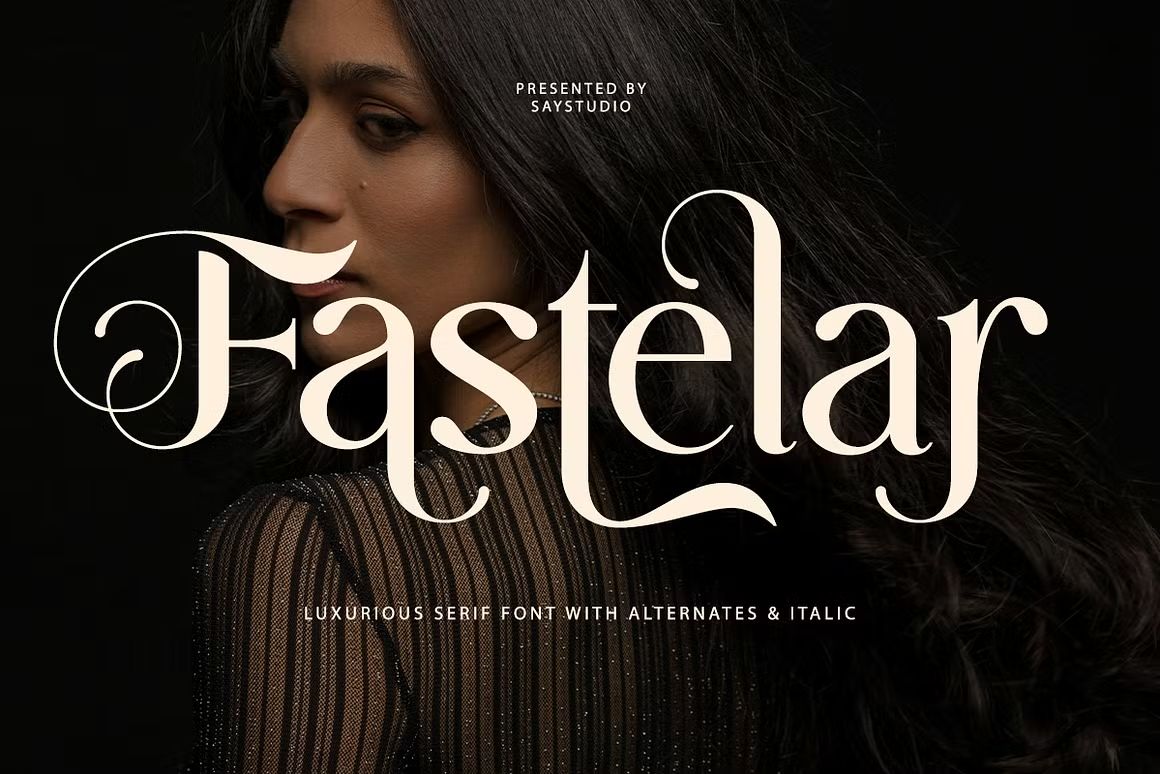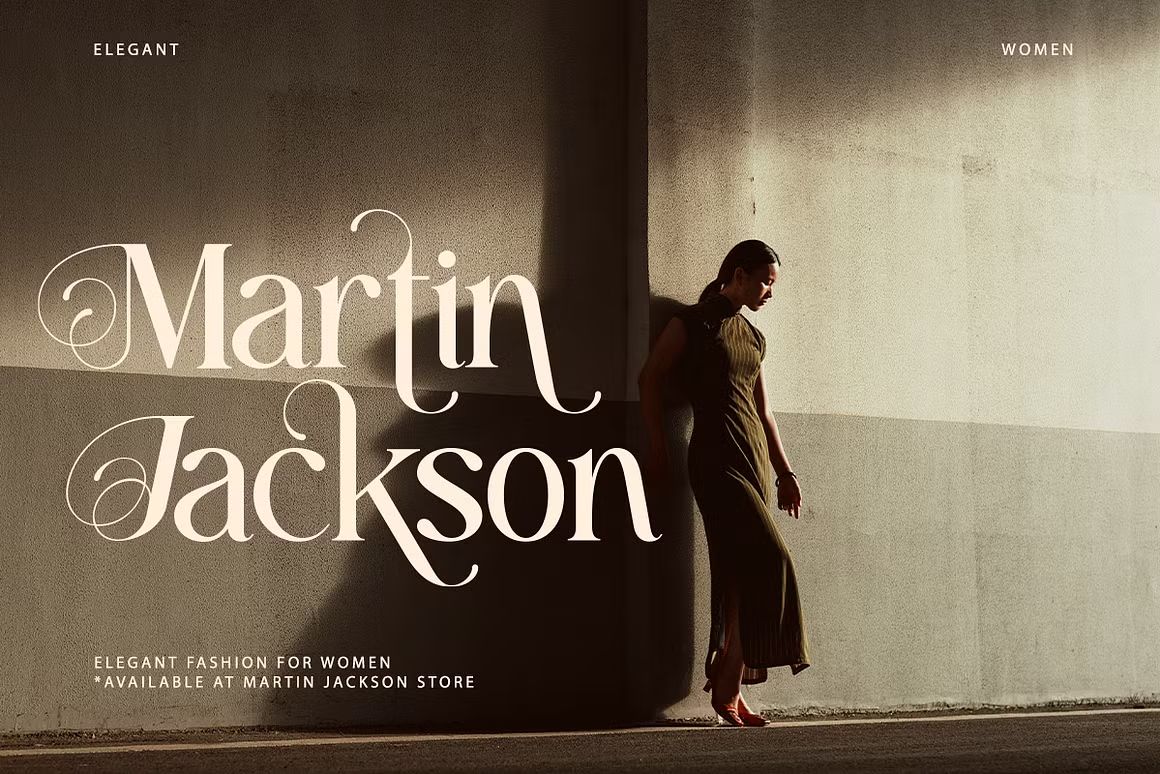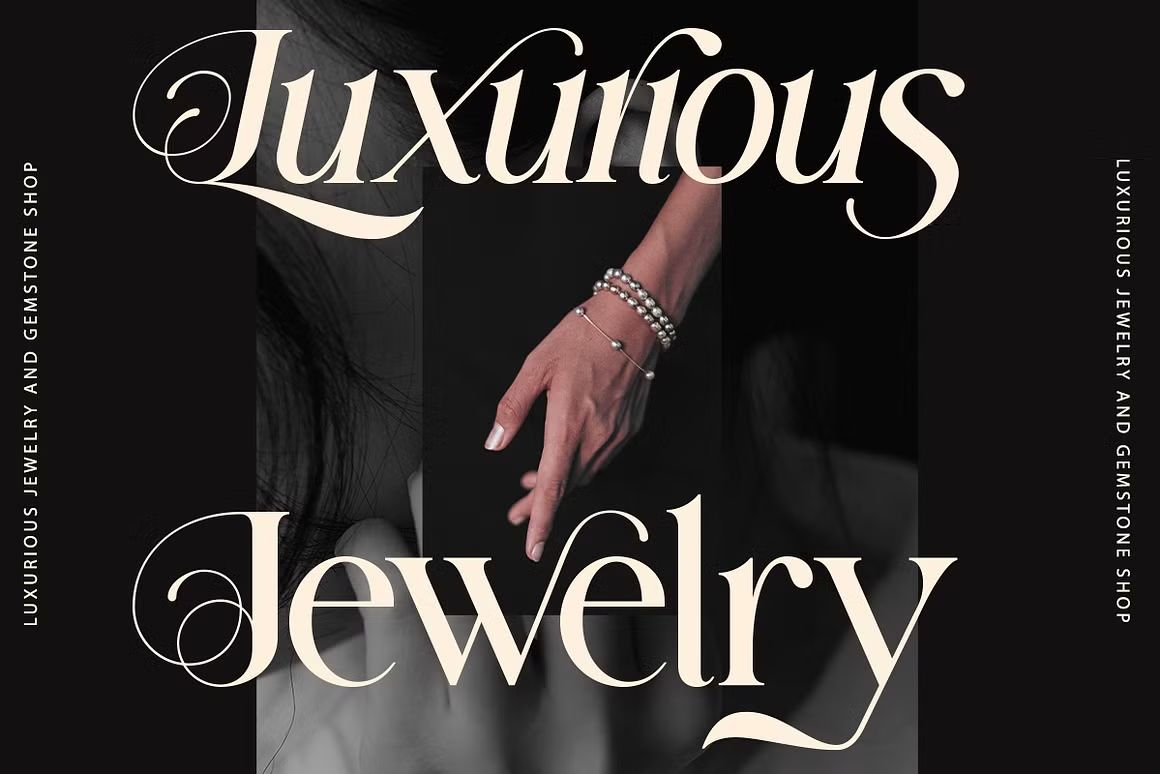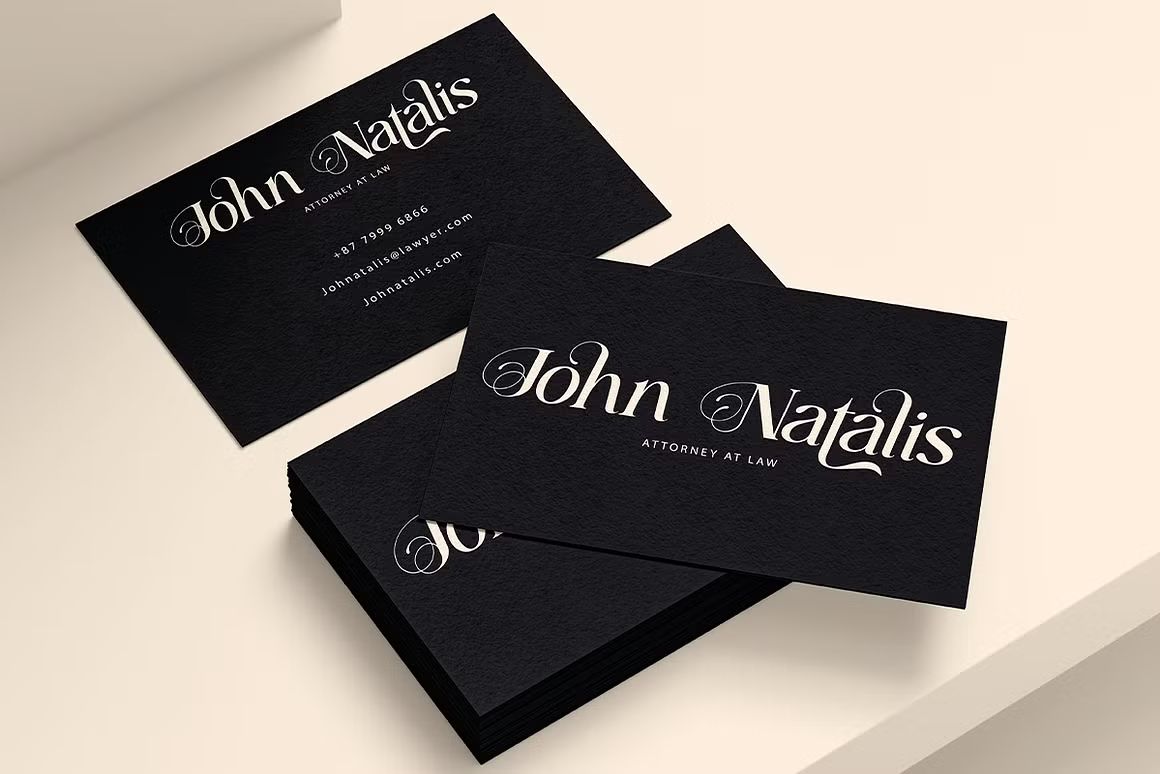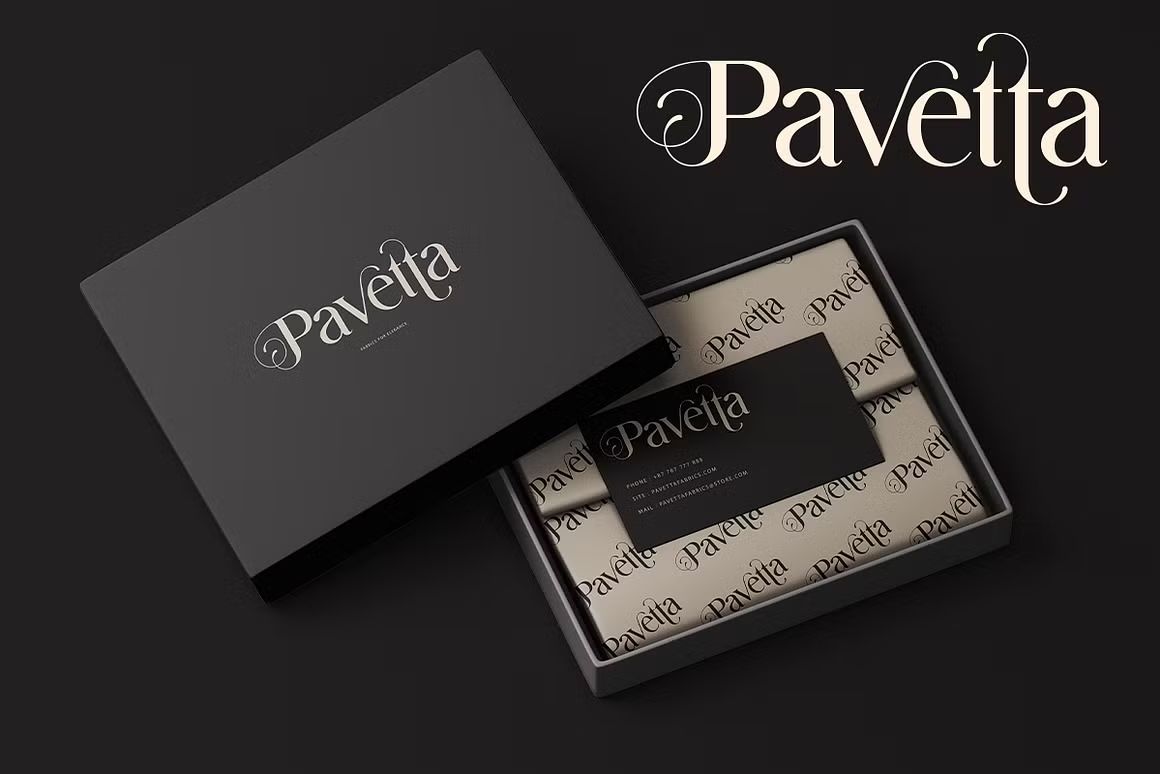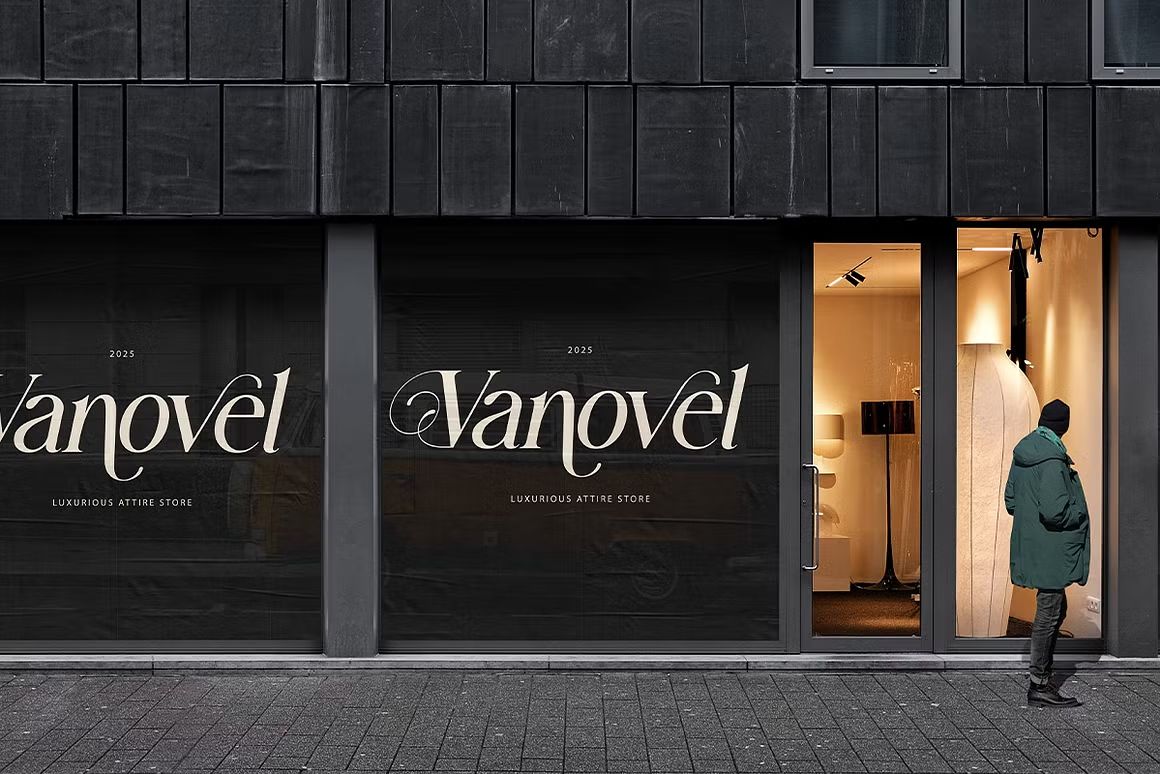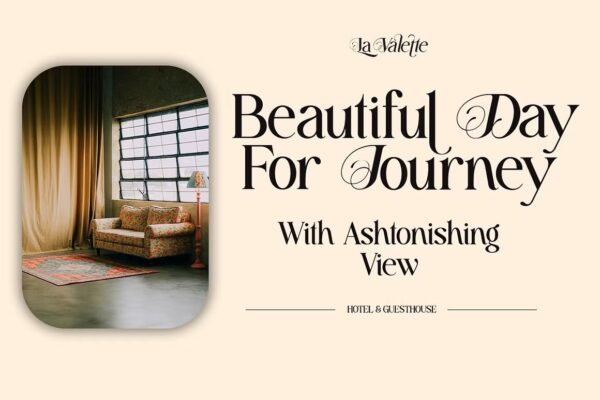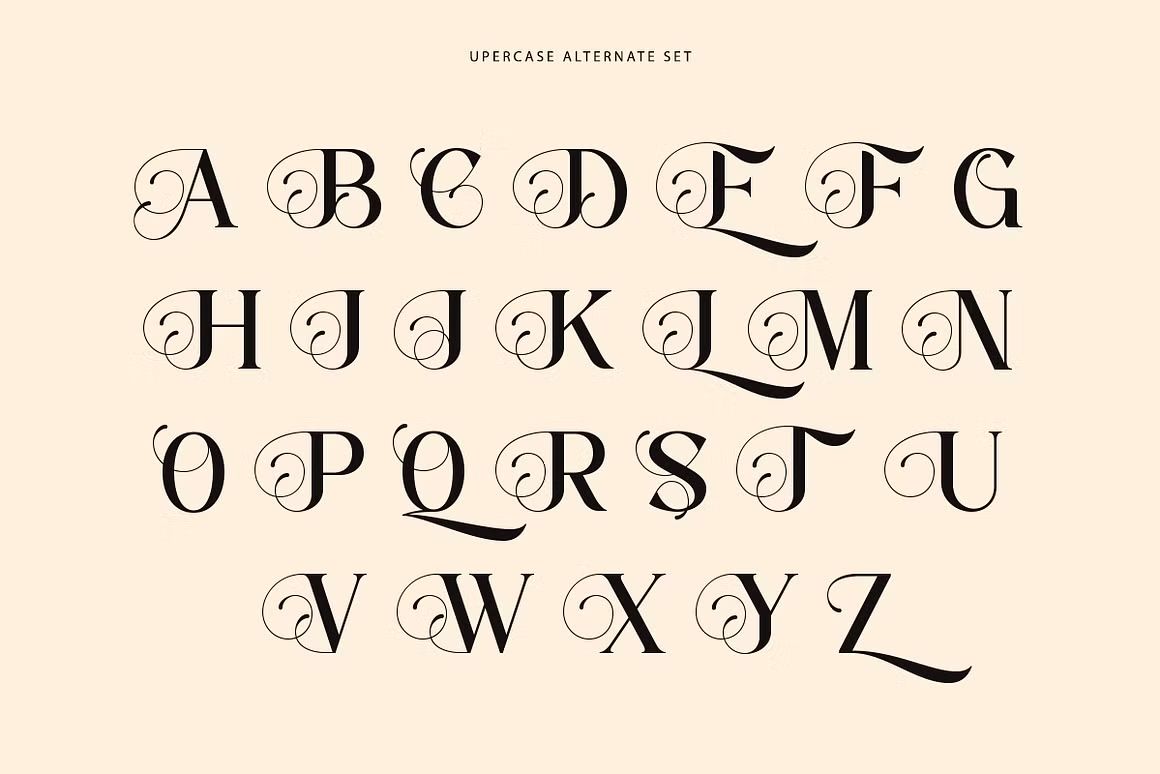
Fastelar – Sans Serif Font
Fastelar adalah font sans serif modern dan bersih, cocok untuk branding dan desain profesional. Format OTF/TTF/WOFF, siap digunakan.
Fastelar adalah font sans serif modern dengan desain tegas, bersih, dan berkarakter. Menampilkan bentuk huruf geometris yang proporsional dan tampilan yang mudah dibaca, font ini sangat cocok untuk branding, editorial, UI/UX, kemasan produk, dan desain profesional lainnya. Fastelar memberikan nuansa modern dan minimalis dalam setiap aplikasi desain.
• Sans serif bergaya geometris dan profesional
• Ideal untuk branding, web design, dan editorial
• Termasuk huruf kapital, kecil, angka, dan simbol